Mittelhochdeutsch 1050–1350
Mittelhochdeutsch ist keine einheitliche Sprache: dieselbe frouwe kann auch frowe oder frouve heißen — je nach Dialekt zwischen Bairisch, Alemannisch und Fränkisch.
Erst im 19. Jahrhundert entstand auf Grundlage der staufischen Dichtersprache eine harmonisierte Schreibweise des Mittelhochdeutschen, um die regionalen Unterschiede auszugleichen. Es ist eine künstliche Schriftsprache, die keiner einzelnen historischen Variante entspricht, aber Aussprache und Schreibweise verbindlich macht.
Eine kleine Lesehilfe: e, i, a werden kurz gesprochen, ê, î, â dagegen lang. Als Beispiel klingt im Hintergrund die erste Strophe von „Loibere riesen“ des Minnesängers Witzlaw von Rügen — Originalschrift, harmonisiertes Mittelhochdeutsch und moderne Schrift im Vergleich.
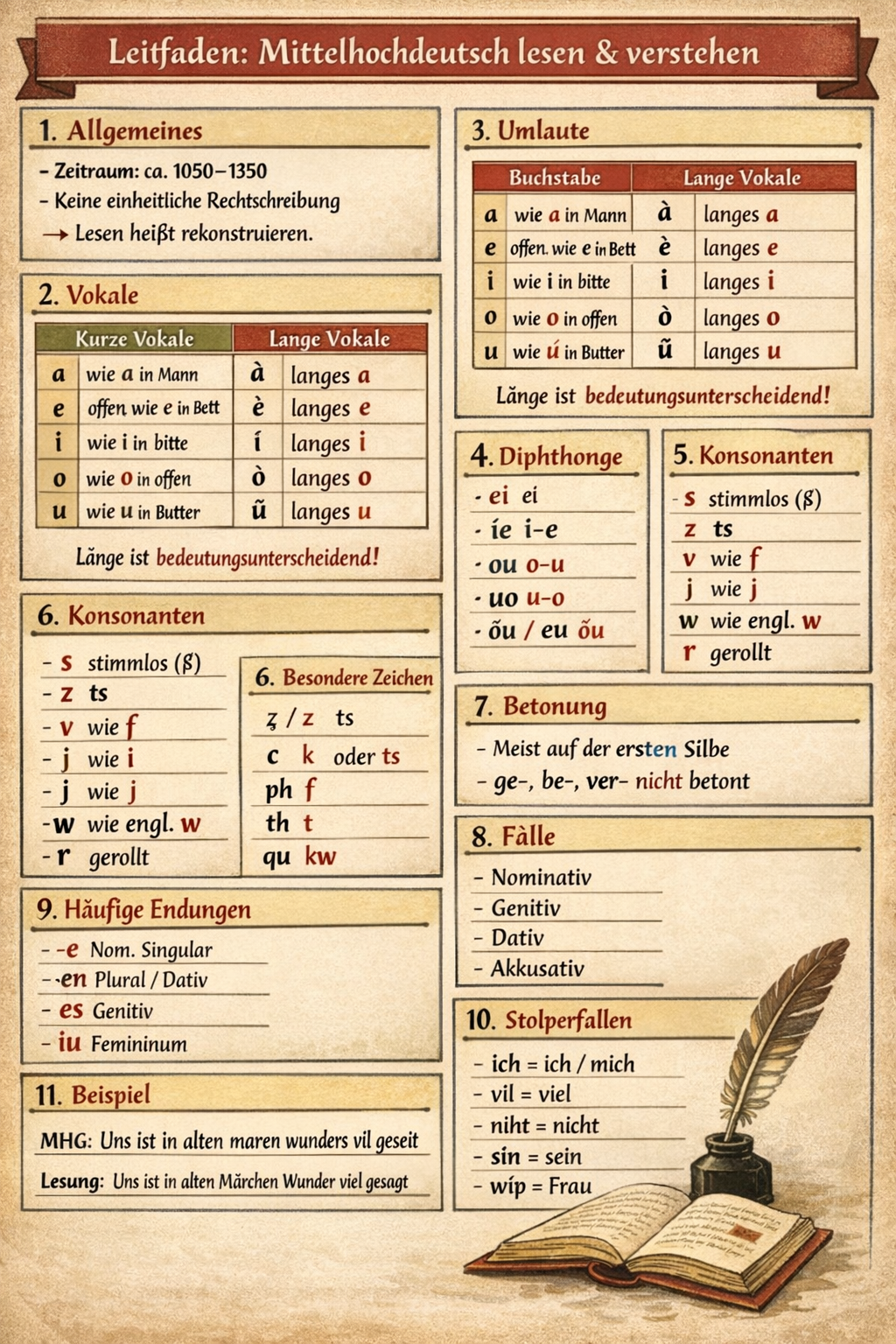
Um 1050–1350
Eine Sprache findet ihre Schrift
Tafel zum Lesen und Sprechen des Mittelhochdeutschen
Lesen & Sprechen
Aussprache in drei Spalten
Wer Mittelhochdeutsch heute lesen will, braucht eine kleine Tafel: kurze und lange Vokale, Sonderzeichen, alte Schreibungen. Original, harmonisierte Form und moderne Übersetzung stehen nebeneinander, damit die Verse wieder zum Klingen kommen.
Mittelalterlicher Schreiber
Im Skriptorium
Der mittelalterliche Schreiber
An schräg gestellten Pulten setzen Mönche und Berufsschreiber Zeile um Zeile aufs Pergament. Jede Region prägt ihren eigenen Stil — Bairisch, Alemannisch, Fränkisch —, und doch wachsen aus diesen Stimmen die großen Werke des hohen Mittelalters.